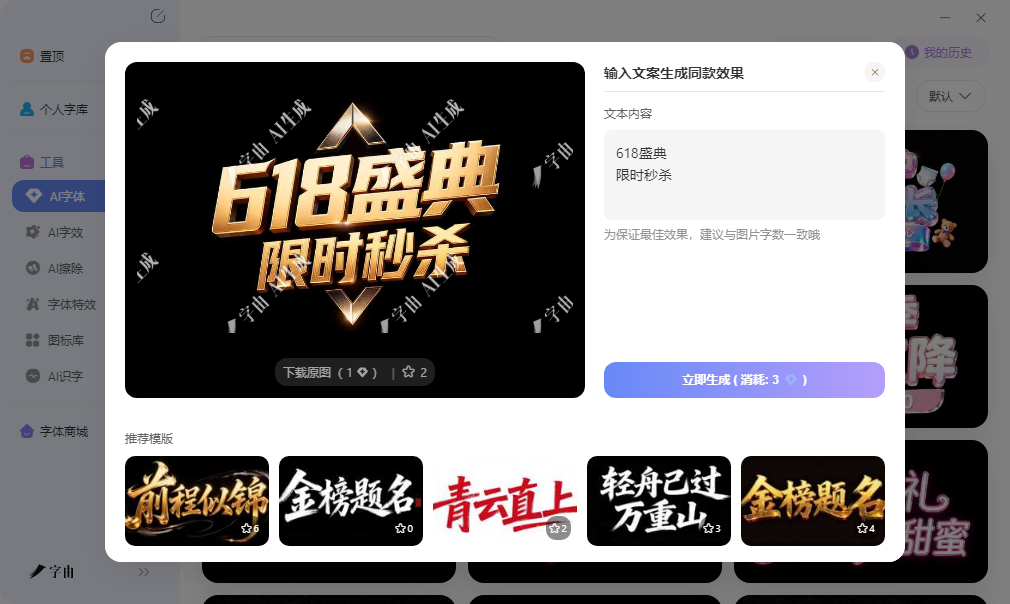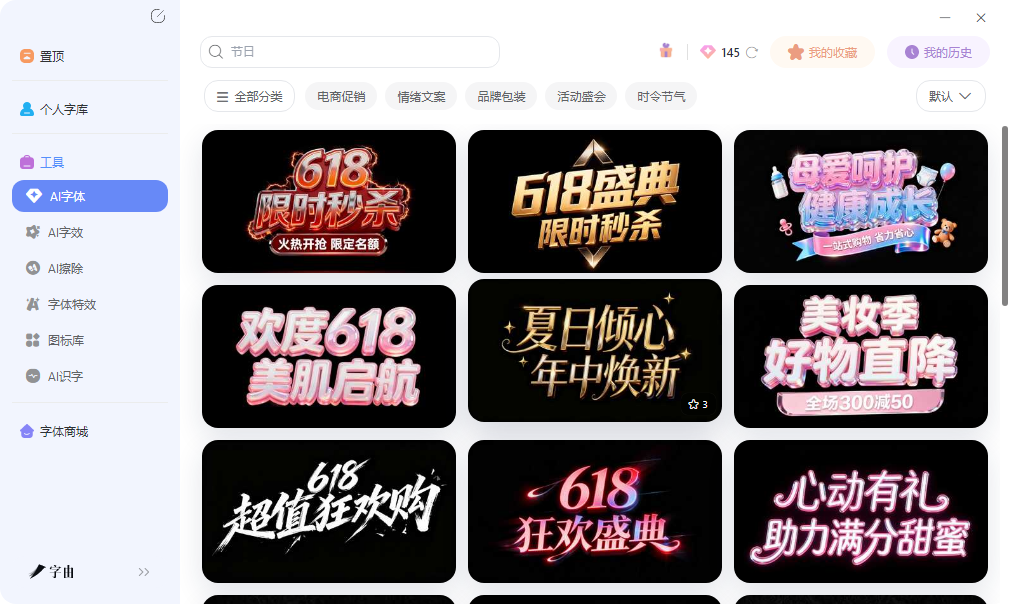
ppt艺术字体下载方案,不用PS也能出特效字
做PPT汇报或者课件时,标题文字往往是视觉焦点,但系统自带的字体选择有限,黑体和宋体用多了显得单调。很多人想做出有设计感的标题,但不会用Photoshop,也不想为了几张标题字专门去学设计软件。其实有不少工具可以直接生成带特效的艺术字图片,保存后拖进PPT里就能用。这篇文章整理的五个ppt艺术字体下载渠道,从中文AI生成到英文在线特效都有覆盖,帮助PPT用户快速获得有设计感的标题素材。
字由对PPT用户比较友好的地方在于,它不需要你懂设计软件也能出效果。客户端里激活的字体,会直接出现在PowerPoint的字体下拉列表中,和Word、Excel里的调用方式一样,选中文字后点一下就能换字体。这个对日常做汇报、课件、方案的人来说比较实用,不需要额外学习成本,操作逻辑和平时排版完全一致。
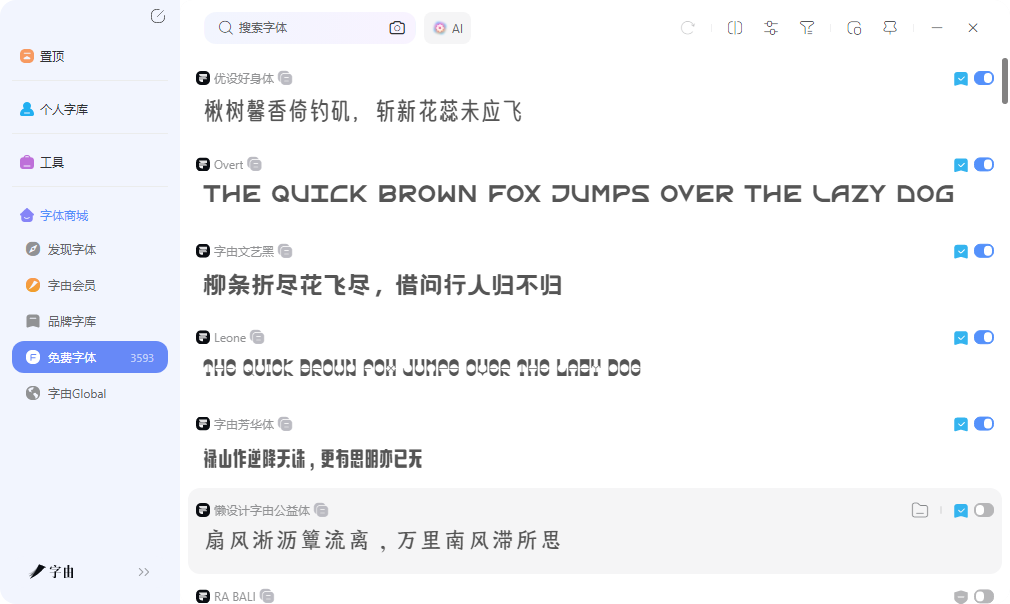
如果PPT里需要的不是纯文字排版,而是一张带特效的艺术字图片,字由的AI字体功能可以直接生成。打开网页版或者客户端,从模板库里选一个风格方向,水墨、鎏金、霓虹、国潮、节日主题等都有覆盖。输入自己的标题文案,大约二十多秒后拿到一张透明背景的PNG图片,直接拖进PPT的幻灯片里就能用,不需要抠图,也不需要调图层样式。对于时间紧、需要快速出方案的职场人来说,这种方式比打开PS一层层调效果要省事得多。
AI字体生成的图片和PPT的兼容性也不错。透明背景意味着可以叠加在PPT自带的背景色或者图片上,不会留下白色方块。如果后续需要调整文字内容,重新生成一张替换即可,PPT里删除旧图、拖入新图,两步完成。免费用户每日有算力额度,登录赠送的点数足够应付日常轻量使用,做几页汇报的标题完全够用。
字由的字体库对PPT场景也有不错的覆盖。商务汇报需要稳重的黑体和宋体,品牌介绍需要有个性的展示字体,教育课件需要清晰易读的正文字体,节日活动需要活泼的手写体,这些在库里都能找到。免费商用的超过三千款,卡片上直接标注授权信息,做公司内部汇报或者对外商业提案时,不用担心字体授权的问题。
2、FontMeme
FontMeme是一个综合性的字体工具站,除了在线文字效果生成外,还提供了字体识别功能。文字效果生成部分按主题做了分类,比如电影海报风格、游戏风格、品牌Logo风格等,用户可以选择对应的主题,输入自己的文案后生成相似效果的图片。
这个工具对PPT用户比较实用的是主题化生成。做电影赏析课件时,可以直接生成电影海报风格的标题;做游戏行业汇报时,可以生成游戏UI风格的文字。FontMeme作为ppt艺术字体下载的渠道,其优势在于主题明确、效果还原度高,生成的图片直接拖进PPT就能营造出对应的氛围。网站上还会展示每种效果的灵感来源,帮助用户判断是否符合自己的项目需求。
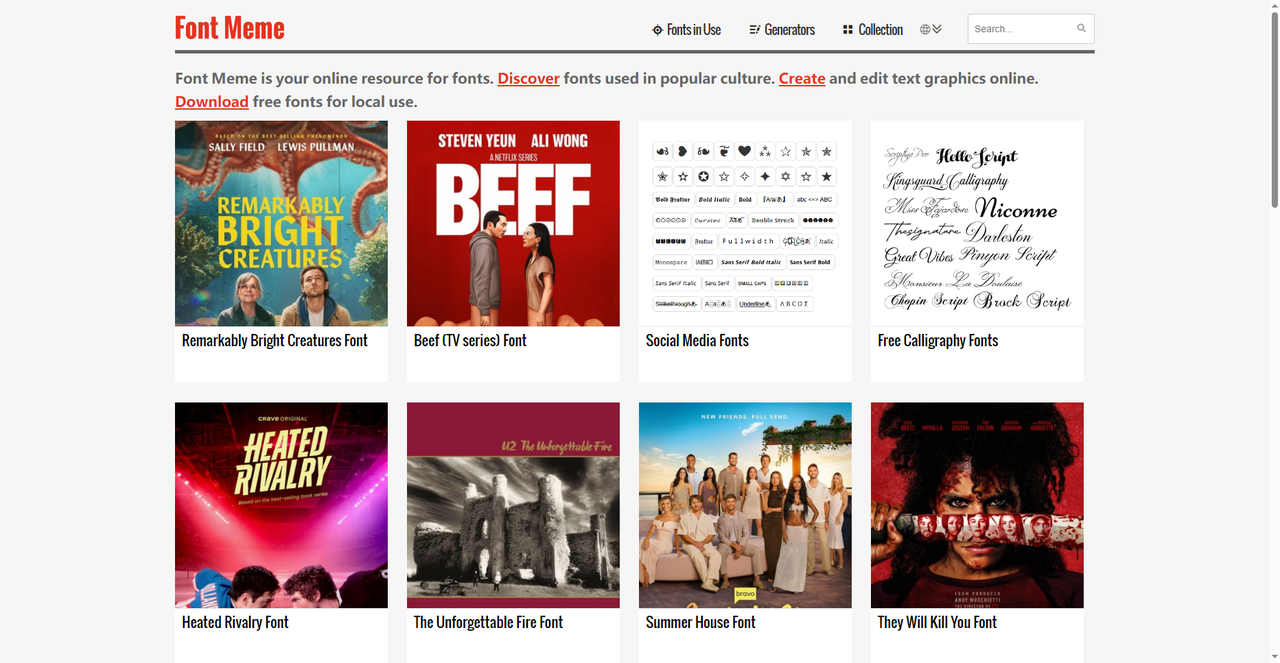
3、TextGiraffe
TextGiraffe的定位偏向可爱和创意风格,适合儿童教育、亲子活动、文创展示等轻松活泼的PPT场景。网站上提供了多种艺术字和Logo生成模板,风格包括卡通、手绘、泡泡、糖果色等,视觉效果比较俏皮。
生成流程和其他工具类似,输入文字后选择风格,系统产出透明背景的PNG图片。TextGiraffe作为ppt艺术字体下载的来源,其特色在于风格独特,很多效果在常规渠道不太容易找到。做幼儿园课件、儿童产品介绍或者轻松主题的汇报时,这里的字体效果能让PPT更有亲和力。需要注意的是,部分高级效果需要付费解锁,免费版本的基础效果对一般PPT场景也够用了。
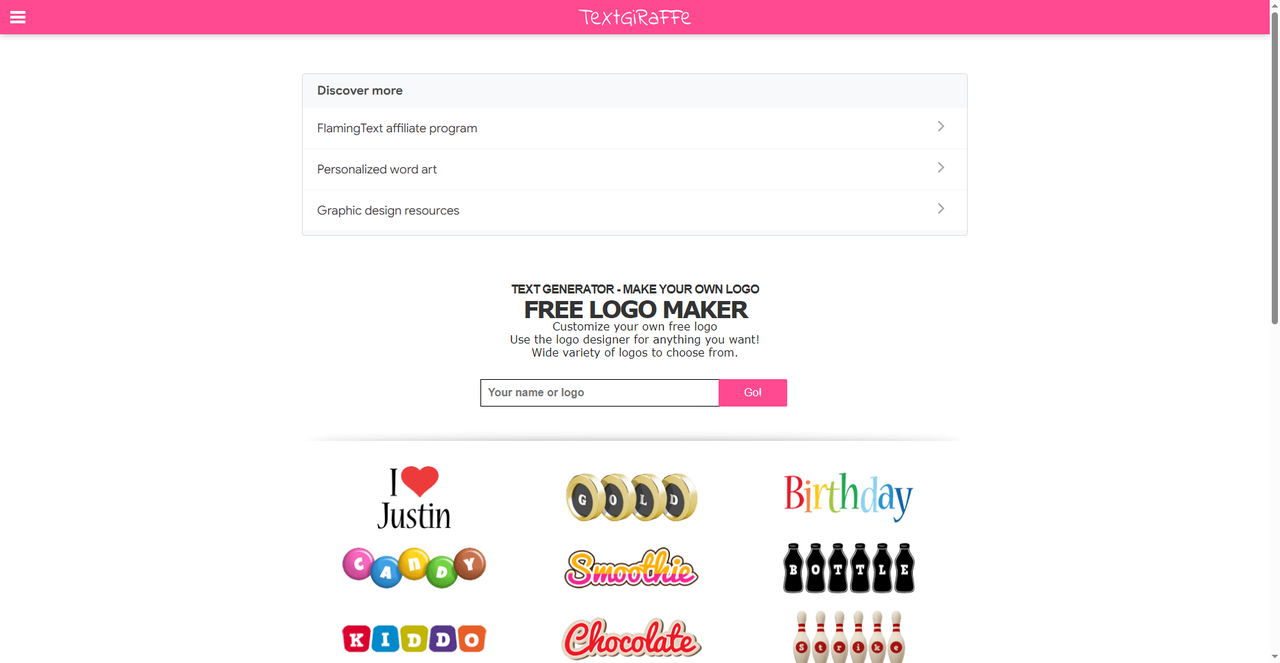
4、Cool Text
Cool Text是另一个老牌在线图形生成器,提供了超过一千种字体特效模板。和FlamingText不同,Cool Text的风格更偏向平面化,阴影、描边、渐变等效果比较多,适合商务和日常场景。网站按风格做了分类,3D Outline、Burning、Chrome、Gradient等标签可以快速定位。
操作流程很直接:输入文字、选择字体和效果、调整颜色、生成图片。生成的PNG图片背景透明,直接拖进PPT里叠加在背景上。Cool Text作为ppt艺术字体下载的渠道,其优势在于模板数量多、风格偏商务、生成速度快。对于需要大量不同风格标题页、又不想打开PS的PPT用户来说,这里的模板库足够应付大部分日常需求。
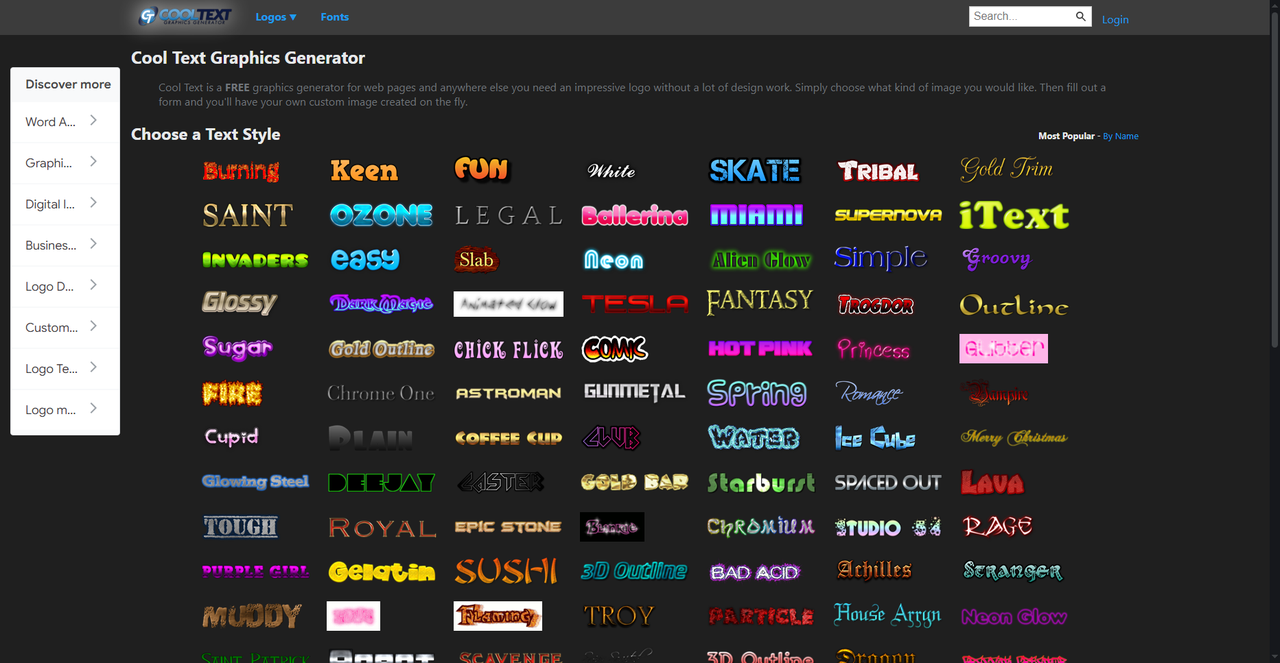
5、FlamingText
FlamingText是一个老牌在线艺术字生成器,专门做Logo和标题特效。网站提供了大量的风格模板,从金属质感、火焰效果到3D立体、霓虹发光都有覆盖。用户输入文字后,选择喜欢的风格,系统会生成一张带特效的图片,可以下载为PNG格式。
这个工具对PPT用户比较友好的是操作简单,不需要任何设计基础。生成后的图片背景透明,直接拖进PPT就能用。网站上还提供了动画版本的生成选项,虽然PPT里用不到动画,但静态图片的质量足够做汇报标题。FlamingText作为ppt艺术字体下载的来源,其优势在于特效风格丰富,尤其是金属和火焰类效果,在常规字体库里很难找到。免费版本生成的图片会带有网站水印,去水印需要付费,但日常内部使用带水印的版本也够用。